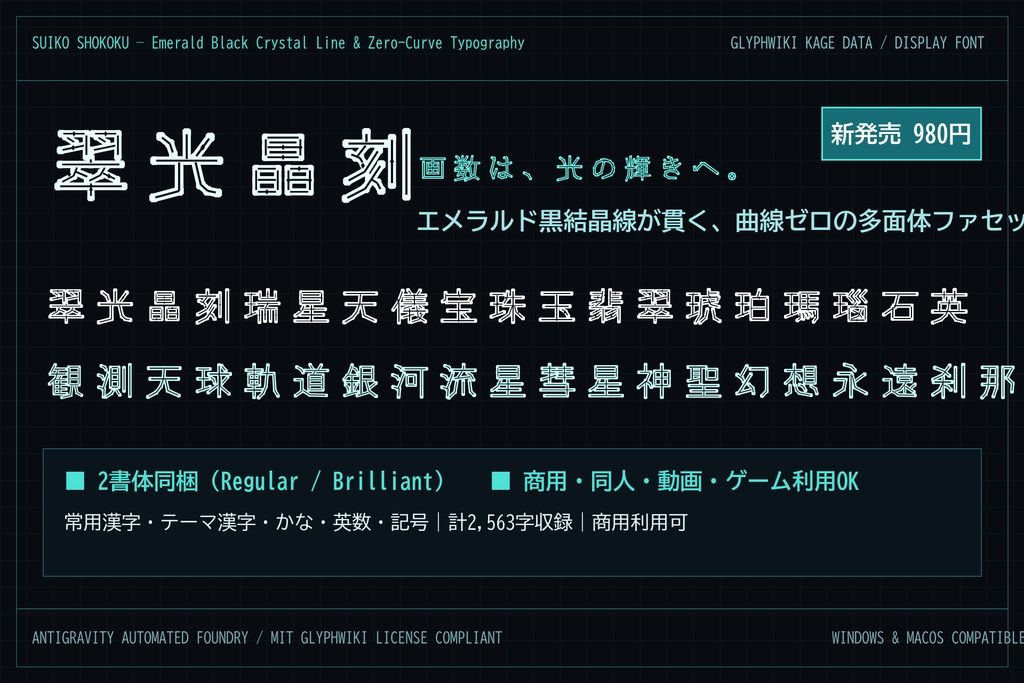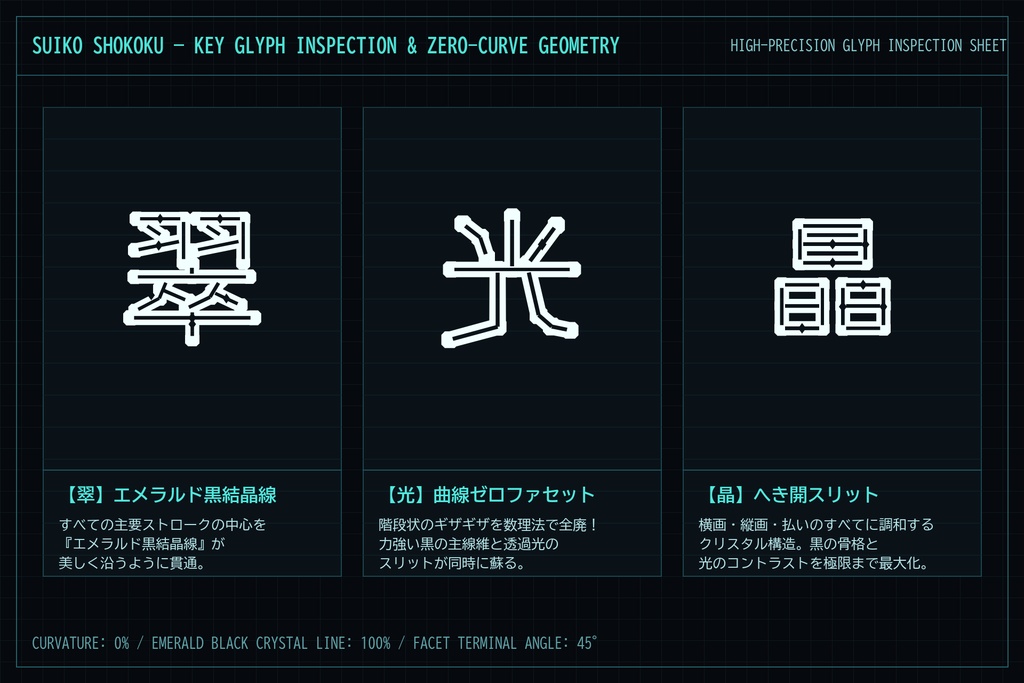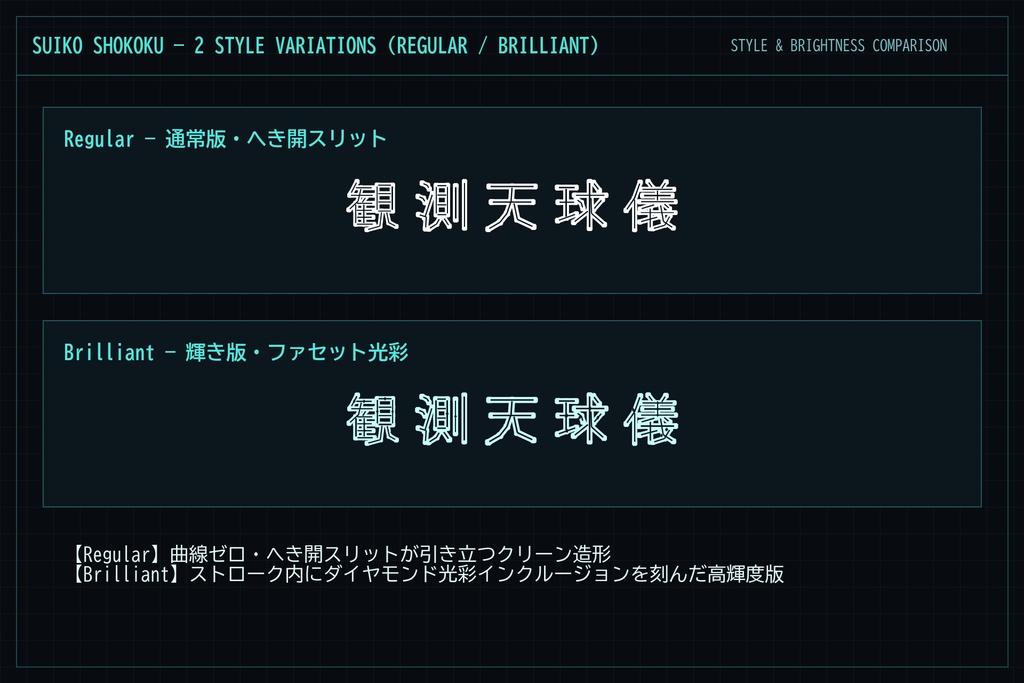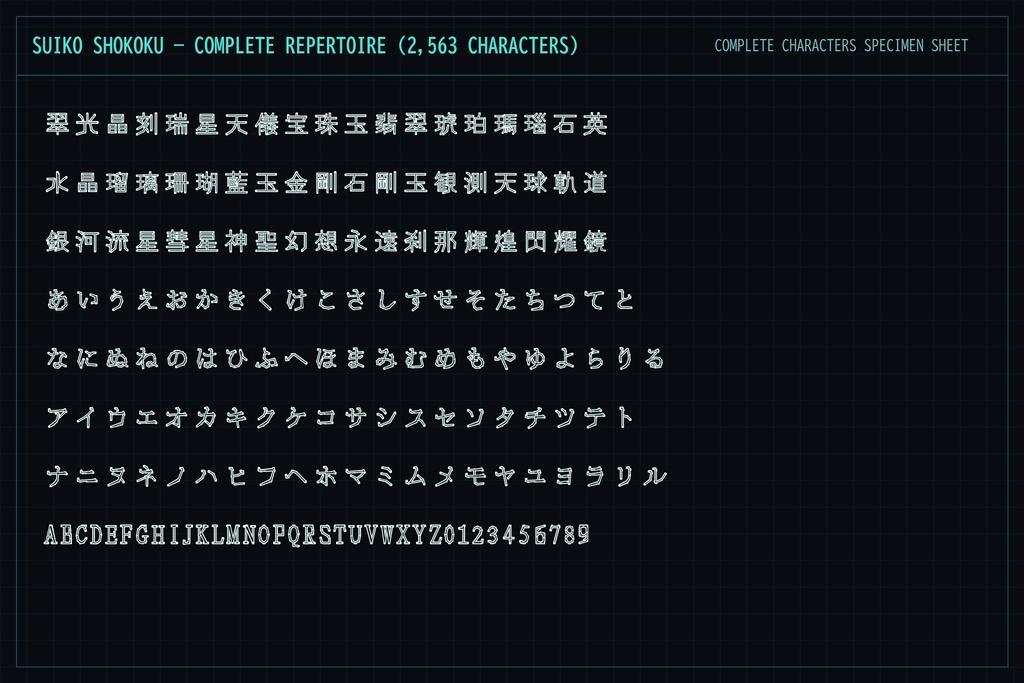
【エメラルド黒結晶線×曲線ゼロ】翠光晶刻|多面体ファセット日本語ディスプレイフォント2書体
画数は、光の輝きへ。エメラルド黒結晶線が貫く幾何学ファセット文字造形。 「翠光晶刻(すいこうしょうこく)」は、鉱石の「へき開(Cleavage)」と「多面体ファセット(Emerald Step-Cut)」を文字構造に織り込み、すべての主要ストロークの中心を「エメラルド黒結晶線」が貫く極上の和文ディスプレイフォントです。 階段状のギザギザを数理アルゴリズム(Douglas-Peucker法)により全廃したクリーンな「曲線ゼロ」折れ線と、中心を走るスリットが光と影の圧倒的なコントラストを生み出します。 ■ バリエーション(2書体同梱) ・Regular(通常版) すべての丸みを直線と45度面取りに結晶化したクリーンなへき開スリット仕様。 ・Brilliant(輝き版) ストローク内にダイヤモンドファセットの光彩インクルージョンを加えた高輝度仕様。 ■ 収録内容 ・常用漢字・追加テーマ漢字を含む計2,563字 ・ひらがな / カタカナ / 半角・全角英数字 / 句読点・主要記号 ・TrueType(TTF)2書体同梱 ■ おすすめの用途 ・VTuber・配信サムネイル、ロゴデザイン、同人誌・ノベルのタイトルロゴ ・ゲームUI、SF・ファンタジー系タイトルグラフィック、MV・動画テロップ ■ ご利用条件 個人・法人の商用利用OK。クレジット表記不要。 制作されたロゴ、動画、ゲーム、印刷物、配信、同人・商業作品に自由にご使用いただけます。 フォントファイル自体の再配布・共有・販売・転売は禁止です。 ※本商品はGlyphWiki KAGE骨格データを独自の多面体結晶アルゴリズムによりフルスクラッチ生成したオリジナルフォントです。MIT/GlyphWiki利用許諾に準拠しています。 ■ フォント試し打ち https://yamatana-font-room.pages.dev/